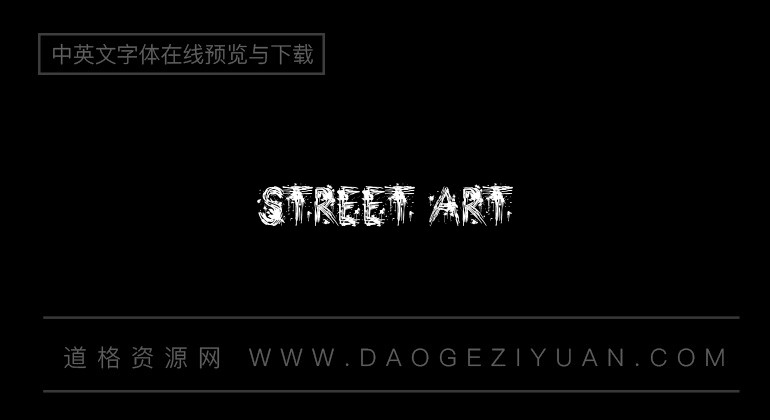
Street Art字体是一种免费的涂鸦和涂鸦风格的艺术字体。它充满了涂鸦和涂鸦的特征,这使得它非常适合用于与街头艺术相关的设计和项目中。它具有粗糙,不规则和抽象的特点,可以让你的设计有一种独特的、富有创意的感觉。 Street Art字体包含大写字母、小写字母、数字和标点符号。它还具有许多不同的变体,这些变体可以用来为单词和短语添加一些额外的创造性效果。这些变体包括字母的变形、连接和填充效果,这些都可以让你的设计更具个性和创意。 Street Art字体适用于各种设计场景,如海报、宣传单、标志、书籍封面等,特别是对于那些关注艺术、文化和创造性的项目来说。内容介绍
Street Art是一款非常不错的手写艺术字体,具有很好的视觉感,适合于文化类的宣传设计、商业类品牌的广告和产品包装设计以及个性化文字排版等较多场景。